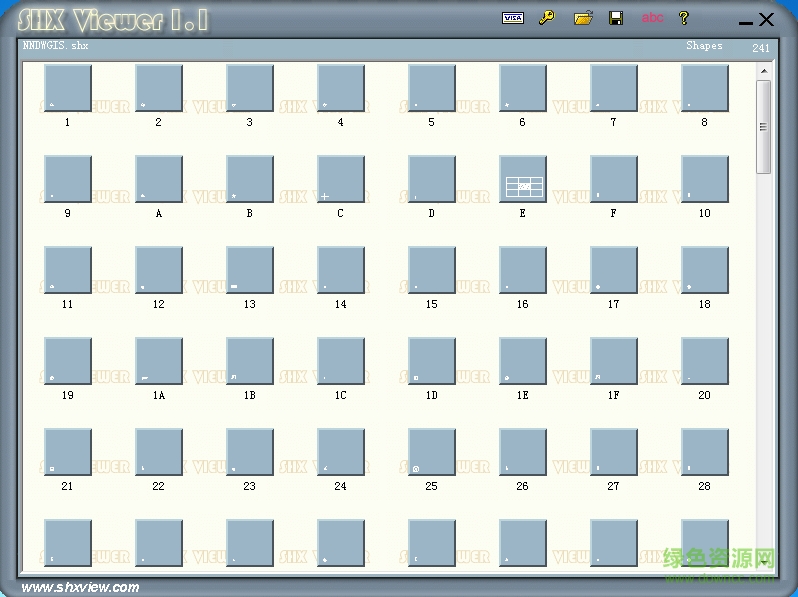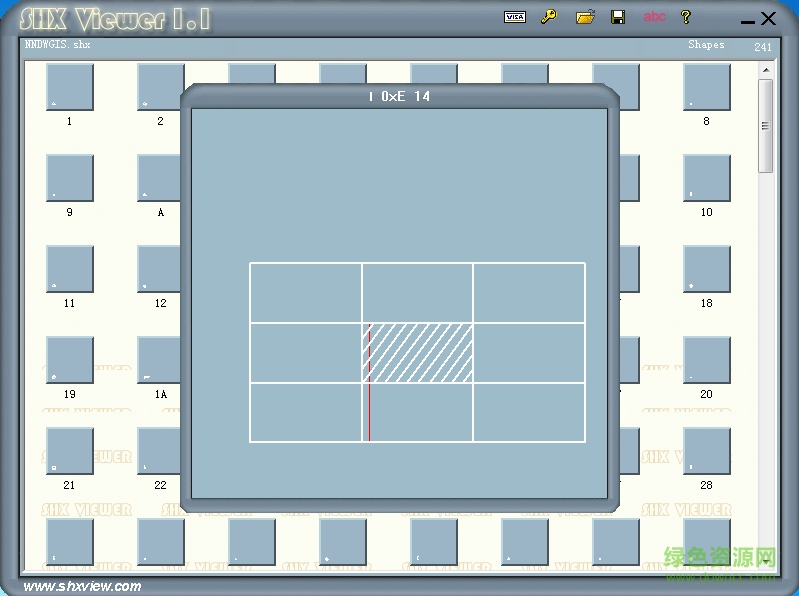
nndwgis.shx是一款有著241個字符的shapes字體,也叫行字體,以點符號為主,百種造型給你最合適的標記選擇,如果你喜歡這款cad字體,來綠色資源網(wǎng)即可免費下載喲!
nndwgis.shx字體介紹
shx、.shp:字體文件,是一種用矢量描述的形文件,shx專門的中文字庫,這種字庫的文件擴展名為.SHX,autocad中用戶可自己定義擴展名為 “ .shp”形定義字體文件。
nndwgis.shx形字體(SHX)的特點
在刷新視圖或平移文字時,屏幕顯示速度更快
文字簡單明晰,處理起來不易出錯。
由線條組成的空心字體,結(jié)構(gòu)十分簡單,占用儲存空間小
形字體說明
形字體,后綴是SHX的一類字體,是CAD專有的字體,安裝在CAD目錄下的“Fonts”文件夾中。圖中所示的形字體(SHX)只能對除亞洲語言以外的字體有效果。